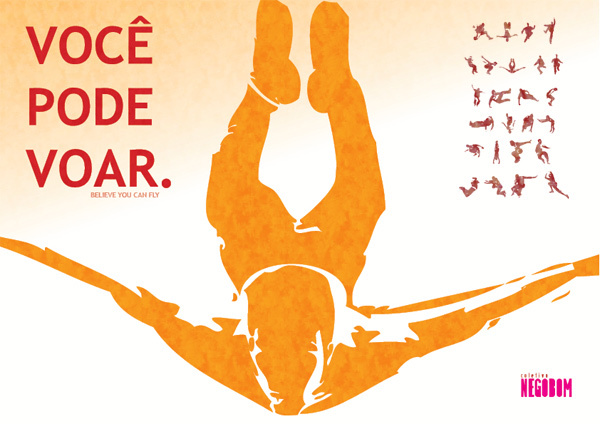
Parkour - L art du deplacement, stworzony przez Felipego Caroé i Dioga Mirandę, to darmowy font dingbat przedstawiający sylwetki do parkouru. Jego postacie uchwycają skoki, przeskoki, stanie na rękach i obroty w powietrzu za pomocą surowych, przypominających tusz konturów. Każda poza emanuje wybuchem ruchu.
Krój ten może przekształcić identyfikację wizualną wydarzeń i plakaty w sekwencję sportowej akcji zamiast zwykłego liternictwa. Artykuły promocyjne i grafika gier również pasują do zróżnicowanych kształtów ciał, które mogą funkcjonować jako pojedyncze ilustracje lub ikony interfejsu. Jego najbardziej oczywistą grupą docelową jest społeczność freerunningowa, zwłaszcza sportowcy i organizatorzy skupieni na ruchu miejskim.